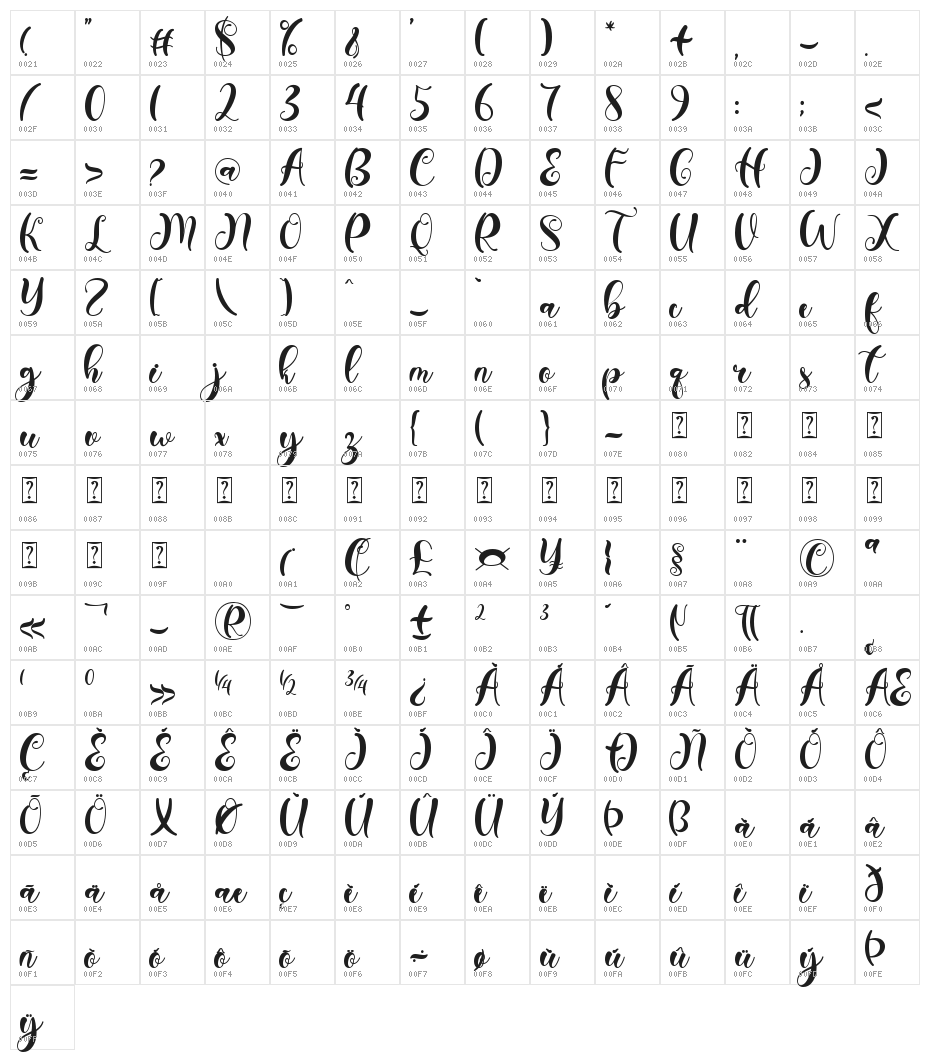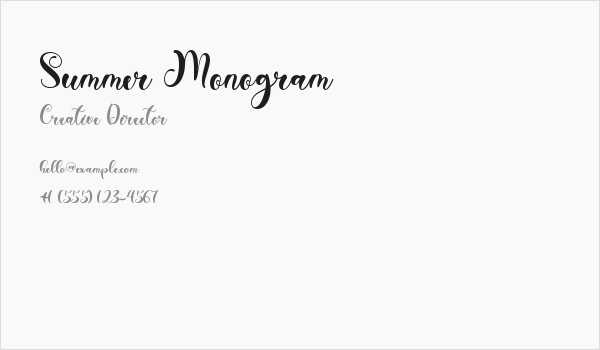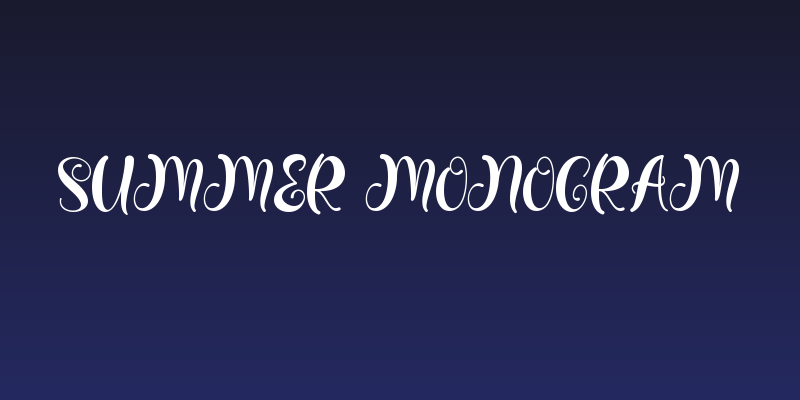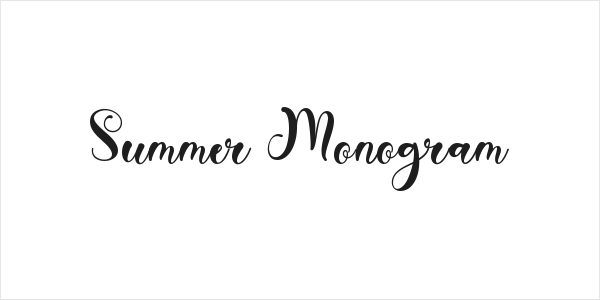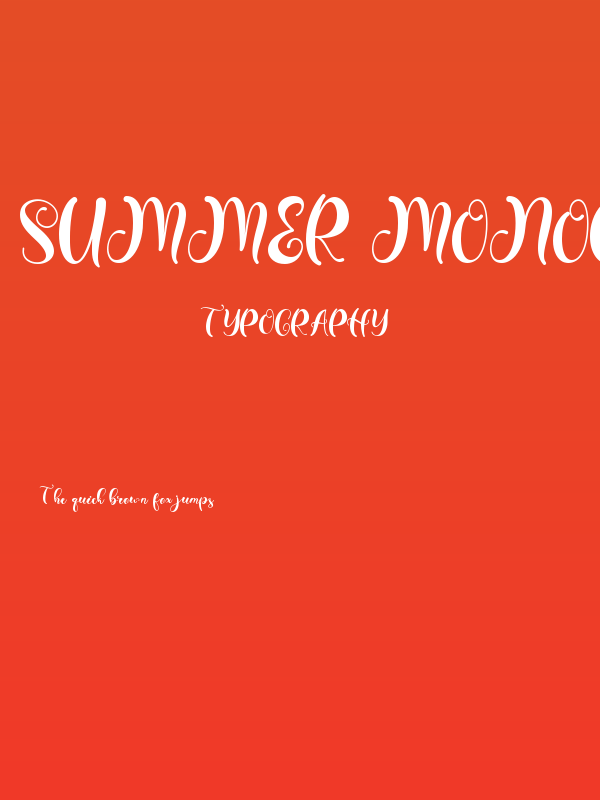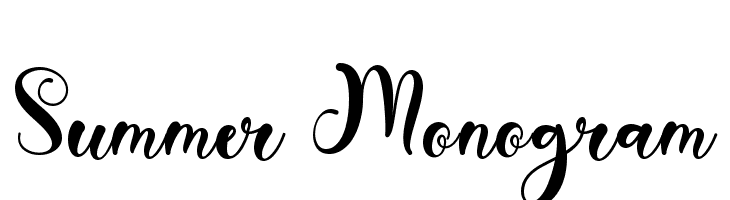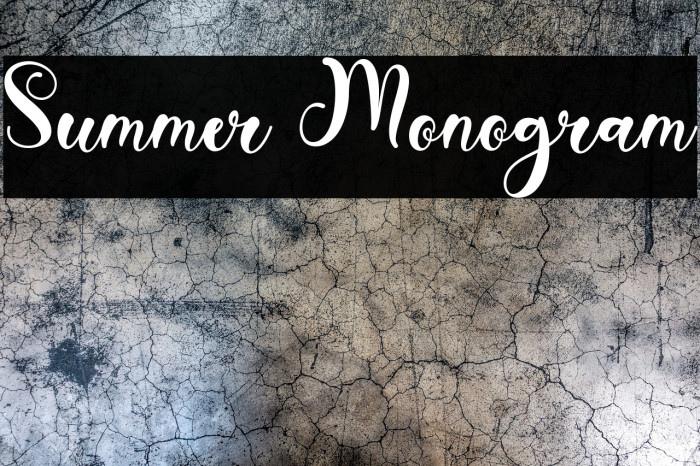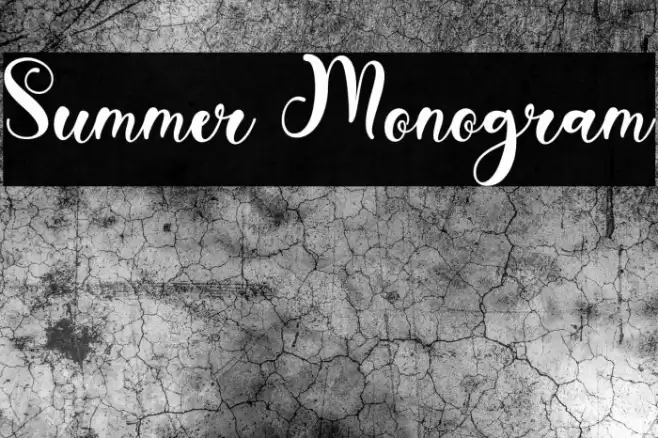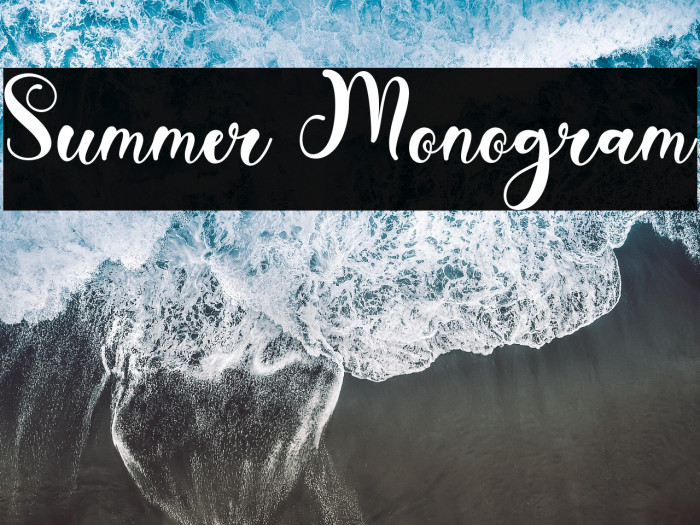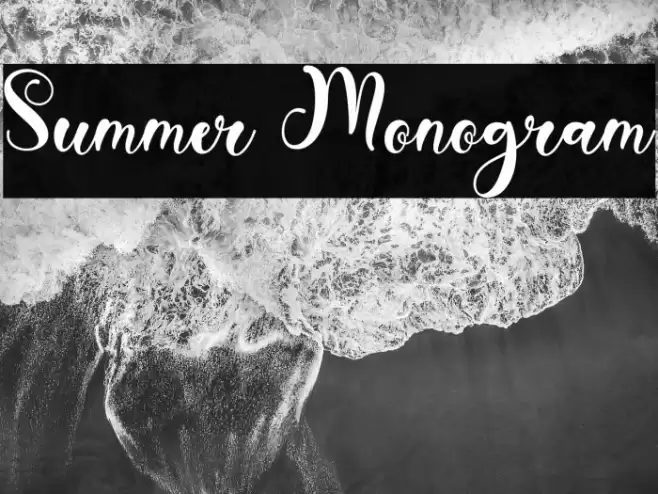
Summer Monogram Font
| श्रेणियाँ | Kids |
| कंट्रास्ट | High |
| समग्र शैली | Decorative |
| उपयोग का मामला | Logos, Headlines, Invitations |
| सुझाए गए प्रोजेक्ट | Ideal for wedding invitations, greeting cards, branding, and decorative signage. |